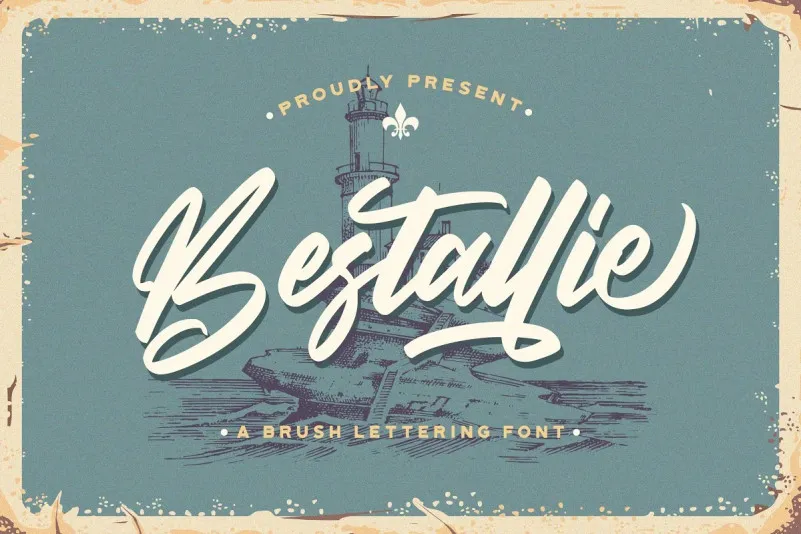
A “Bestallie Font” é uma elegante escolha para quem busca dar um toque único aos projetos digitais. Esta fonte escrita à mão tem um estilo retro e bold, perfeitamente adaptado para headlines e logotipos que buscam destacar-se. Ela traz a essência de um design moderno, sem perder o encanto clássico. A “Bestallie Font” é ideal para quem valoriza a criatividade em sua identificação visual, seja ela web, impressão ou qualquer outra plataforma digital. Sua simplicidade e estilo retro garantem que suas ideias sejam notadas e vivas. Experimente incorporar a “Bestallie Font” em seus projetos mais audaciosos para ver como ela reforça o design de forma única.